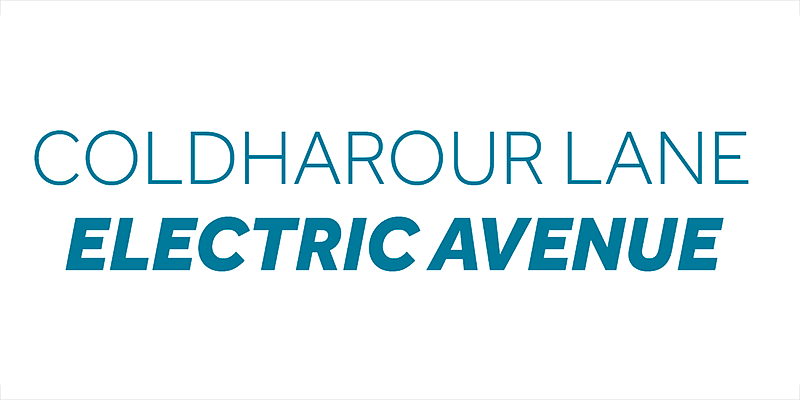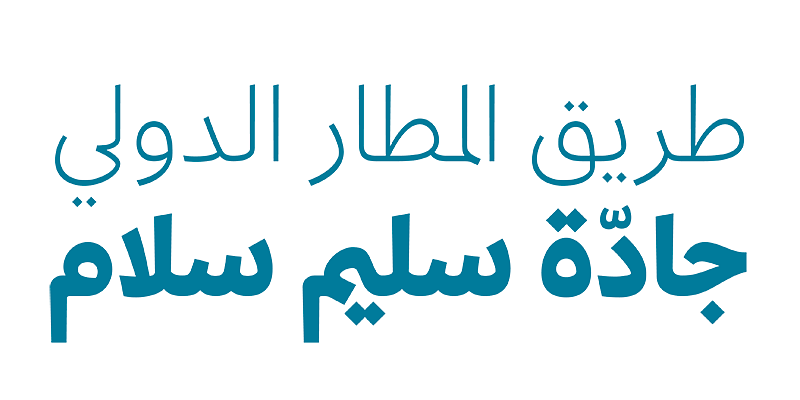
Die Effra kann ihre Familiengeschichte bis zur Caslon Junior zurückverfolgen. Mit ihren klaren Linien und humanistischen Formen ist Effra eine äußerst flexible serifenlose Schriftfamilie, die schnell zu einem Designfavoriten wurde.